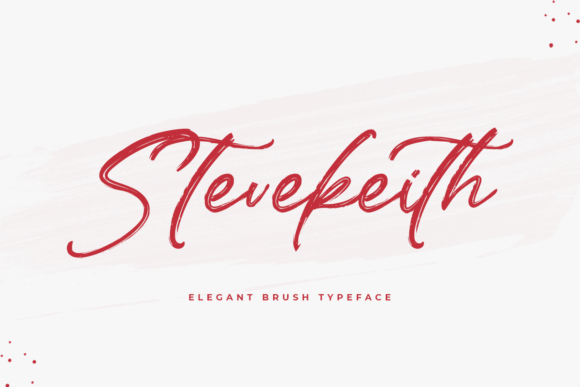
Stevekeith
Việc tìm kiếm các thành phần thiết kế phù hợp có thể là một thách thức, nhưng Stevekeith cung cấp một bộ sưu tập đặc biệt giúp nâng tầm công việc của bạn ngay lập tức.
Cho dù bạn đang tạo sản phẩm POD (In theo yêu cầu), thiệp mời đám cưới hay đồ họa mạng xã hội, Stevekeith đều là một sự lựa chọn lý tưởng.